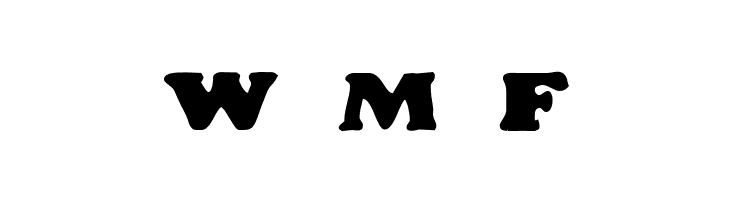
Добро пожаловать в раздел Топ шрифтов — здесь популярность встречается с качеством. Это самые скачиваемые и используемые шрифты нашего сообщества за этот год. Если нужны надежные варианты для логотипов, сайтов или соцсетей — начните отсюда.
Каждый топ‑шрифт отличается балансом, читабельностью и универсальностью. Здесь есть современные гротески, изящные скрипты, винтажные антиквы и минималистичные дисплейные семейства. Если не знаете, с чего начать, раздел «Топ» — ваш короткий путь к проверенной типографике.
( Phitradesign - Philip Trautmann - www.phitradesign-fonts.com )
A cursive, elegant font with a handwritten style and bold, connected letters.
( Typodermic Fonts - Ray Larabie - www.typodermicfonts.com/ )
A bold, italicized font with a dynamic and modern style.
An elegant serif font with high contrast and refined details.
A futuristic, geometric font with bold, interconnected lines and a sci-fi aesthetic.
( Oktora Mila )
A modern, rounded sans-serif font with a clean and approachable design.
( Fonts by Vít Čondák )
A geometric, octagonal font with a modern and technical style.
A playful, hand-drawn font with a sketch-like, textured appearance.
( Fonts by Dieter Schumacher )
A decorative font with characters made of stripes and stars, offering a bold and festive look.
( Brynda1231 Industries )
A pixelated, blocky font with a retro digital aesthetic.
( Fonts by Jeff Bensch )
A playful, dripping font with a gooey, cartoonish style.
A modern, geometric, semi-italic font with rounded edges and condensed spacing.
A playful, rounded font with a hand-drawn, casual style.
( Fonts by Studio Typo )
A bold, eroded font with a vintage, distressed look.
A decorative and distressed font with intricate patterns and textures.
A structured, high-contrast serif font with a classic Roman architectural influence.
A geometric sans-serif font with a clean, modern design and uniform stroke widths.
A bold, geometric outline font with sharp angles and a modern aesthetic.
( Font by Sven Stuber - www.superlooper.de )
A futuristic, minimalist font with thin, geometric lines and a sleek design.
( Fonts by Matthew Welch - www.squaregear.net/fonts/ )
A brush-like, calligraphy-inspired font with dynamic strokes and an exotic aesthetic.
A bold, distressed font with a rugged, textured appearance.
( Design Dojo )
A playful, handwritten font with bold, rounded characters and a whimsical style.
( Jen Jones - www.jenjonesfonts.com )
A playful, handwritten font with flowing, cursive-like letters and a whimsical style.
Какие шрифты в топе прямо сейчас?
Дизайнеры любят hello_love demo, Oldprint, MesmerizeSeEb-Italic, Italian Mosaic Ornaments and Hermia!" за чистые формы и широкий спектр применения — от фирменного стиля до лендингов и постеров.